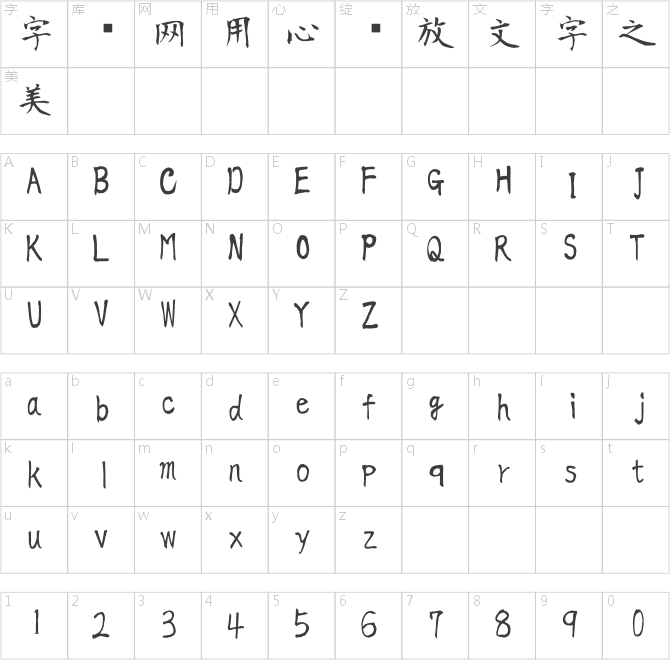
字體介紹 莫大毛筆體是基于衡山毛筆體的開放原始碼中文字型增加更多字重的字數的修改版字體。衡山毛筆字體是來自于日本書法家青柳衡山,目前字型內文字和符號字數在:14,321個。 與衡山毛筆體體有何不同? 1、增加了更多中文字體 莫大毛筆體補齊臺灣教育部列出的4,808個常用字,在原本的衡山毛筆字體架構下,莫大毛筆字體增加(和修改)168個字。 2、增加了字體字重,現在總共5個字重 原本的衡山毛筆字體放在Regular字重裡,現在透過程序自動產生ExtraLight、Light、Medium、Bold 新的字重。Light字重是把原本的KouzanBrushFont微微調細一點點。在ExtraLight的字重裡,可能會因為筆劃太細造成某些筆畫消失。在Medium和Bold的字重裡,可能會因為筆劃太粗造成某些筆畫重疊難以識別,有粗體字的需求,可以先挑戰使用Bold字重看看,如果發現效果不如預期,再改用Medium字重。 不能確定自動產生出來的字重裡每一個都是完整的字,畢盡程式會誤判是常有的事情,所以不是在Regular字重裡的筆劃可能會消失。 3、清除衡山毛筆字體裡空白的文字 衡山毛筆字體裡有很多空白的字, 會造成無法讓系統自動用預設字體來補字,已清除空白的文字。 4、調整標點符號位置 衡山毛筆字體的全形標點符號針對日本做設計,調整為臺灣常見的置中用法。半形的backslash,調整為非日本地區用法。 5、增加部分臺灣口語出現的中文字和增加部份的粵語字 在原本的衡山毛筆字體架構下,莫大毛筆字體增加11字。感謝網友Luke Liu的貢獻,在莫大毛筆字增加86個粵語字。 字體授權 授權出處:https://max-everyday.com/2020/03/bakudaifont/ 這款字體是依據SIL Open Font License 1.1授權協議,可以用于任何用途,包括免費商用。 開放字體許可證(OFL)是由SIL國際維護的。它試圖在自由軟件和字體設計社區的價值觀之間達成妥協。它用于幾乎所有開源字體項目,包括Adobe、Google和Mozilla。